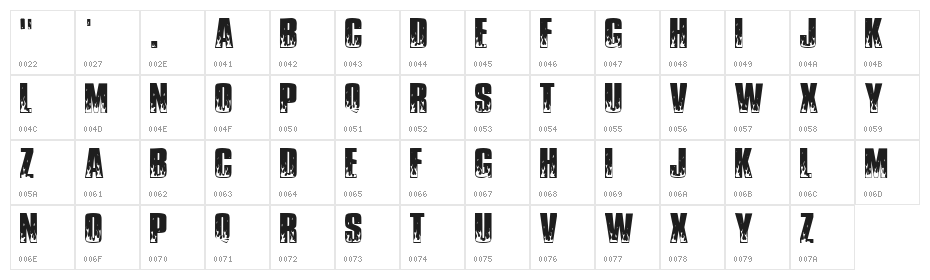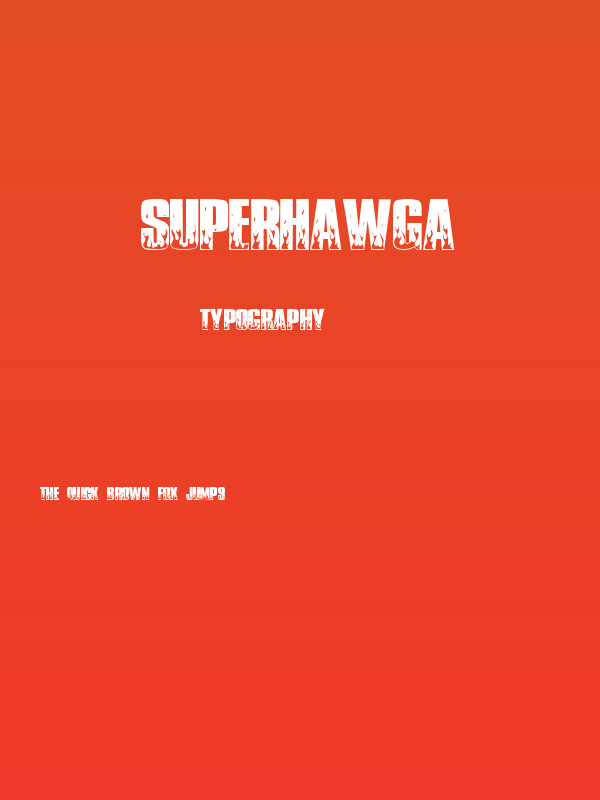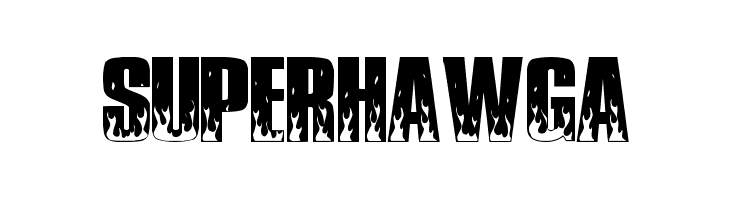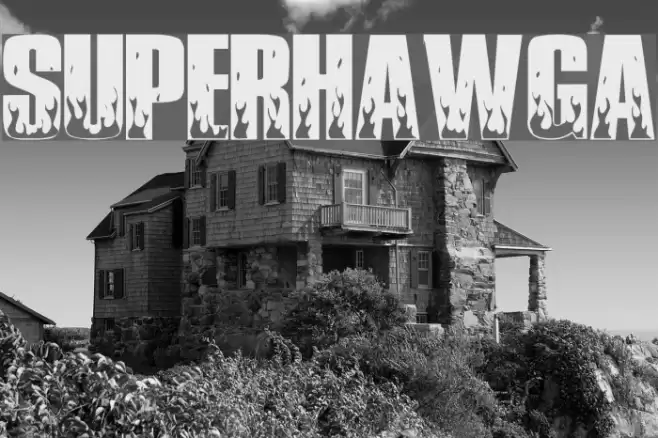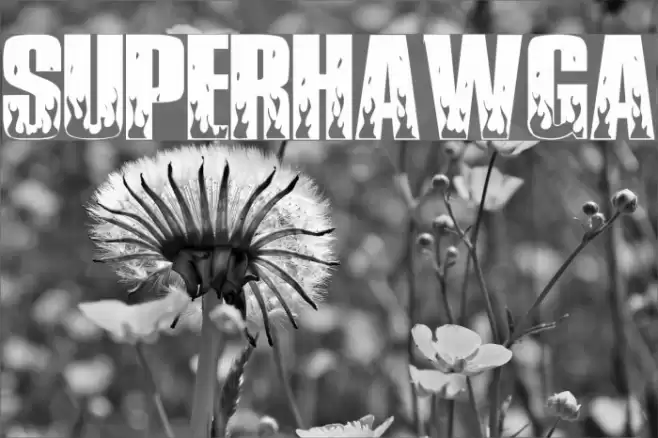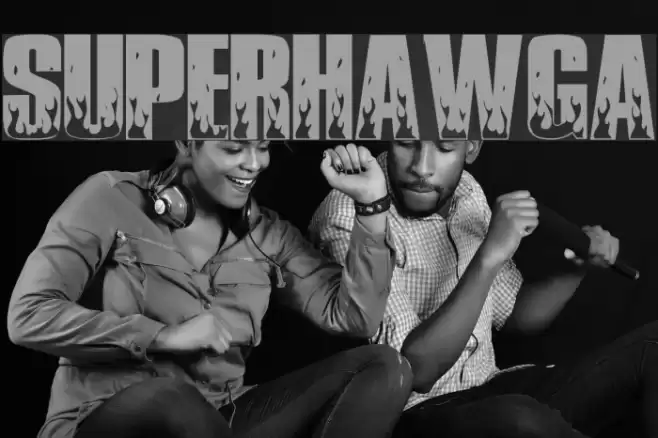
SuperHawgA Font
| Stil general | Modern, Decorative |
| Proiecte propuse | Perfect for event posters, music album covers, branding for extreme sports, or any project needing a bold, fiery aesthetic. |